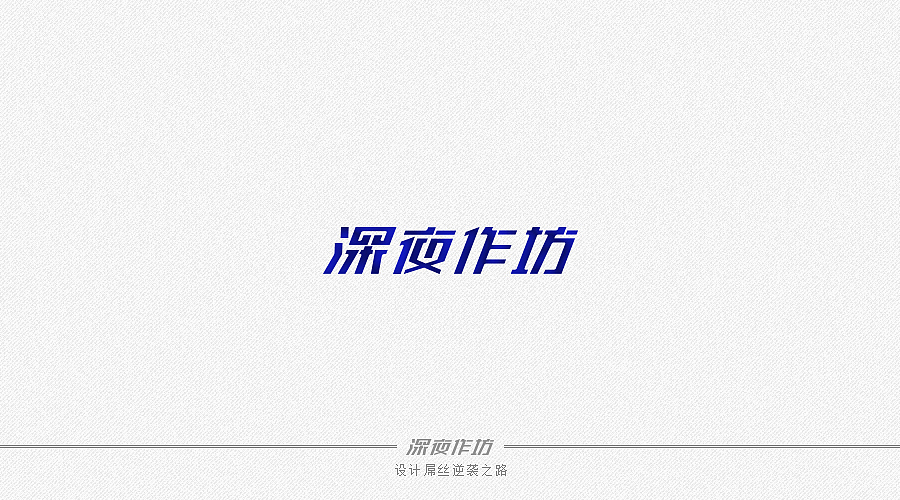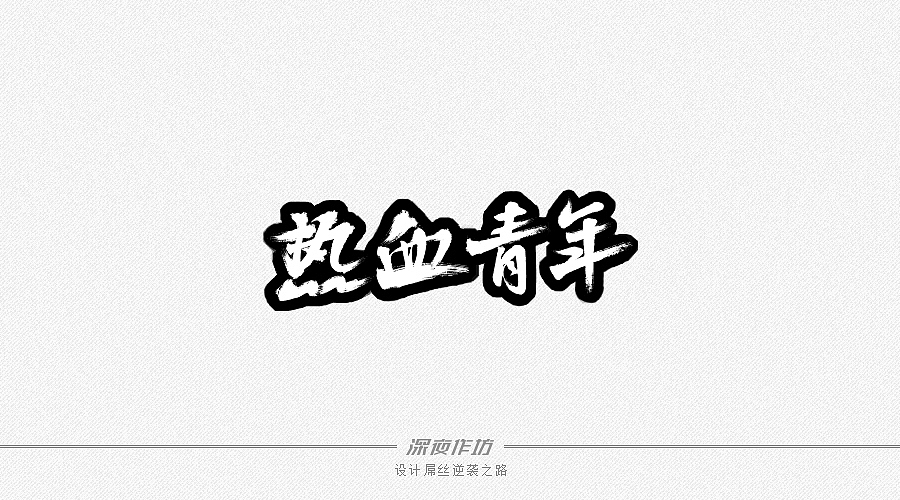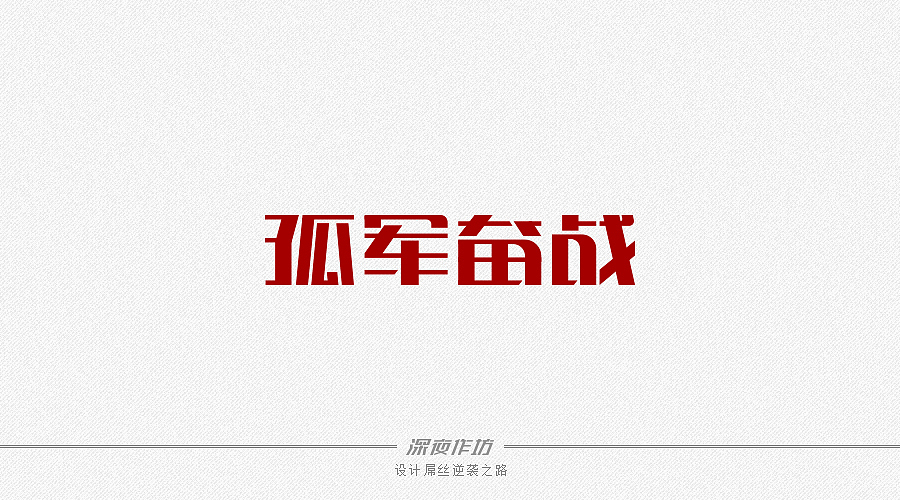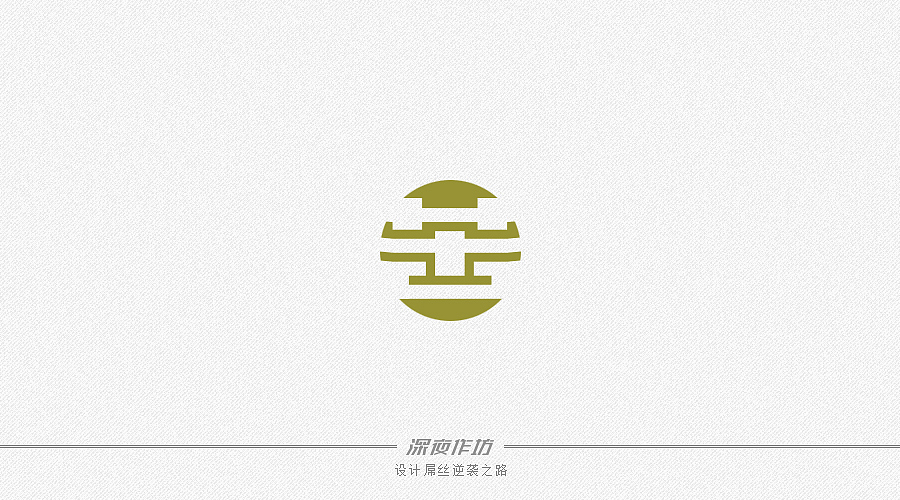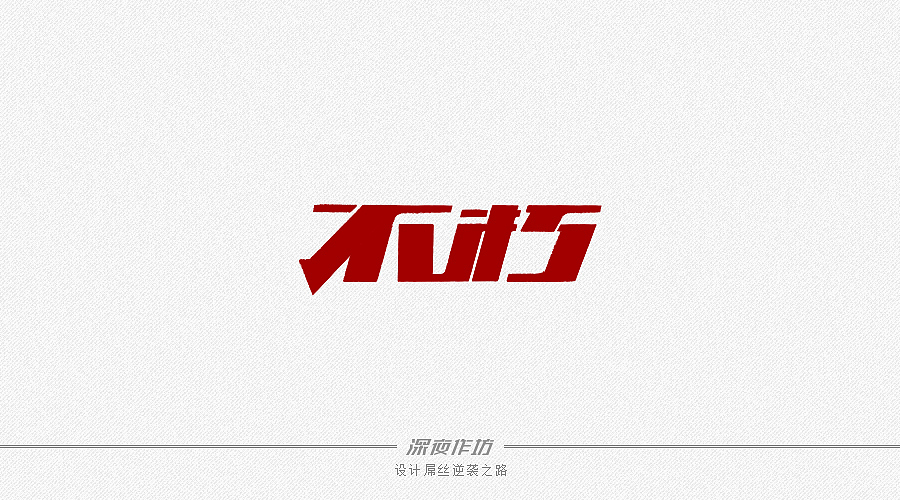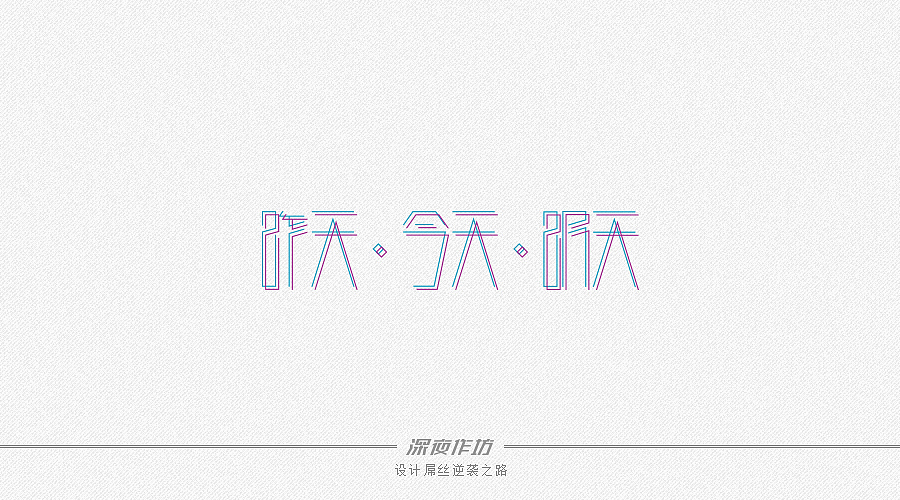
深夜作坊--8月份字体总结
每次做字都做到深夜,故起名“深夜作坊”,有点黑作坊的感觉,哈哈,说多了,上图
我们都是青年,但已经不再热血
一个人的战斗,无所谓辛不幸苦,开心就好
不朽,精神不朽,毅力不朽。
昨天我是个屌丝,今天是个屌丝,说不定明天就变高富帅了,哈哈
自己做字总是一样的风格,沉稳,希望能跳出这个框
这个就不说了。